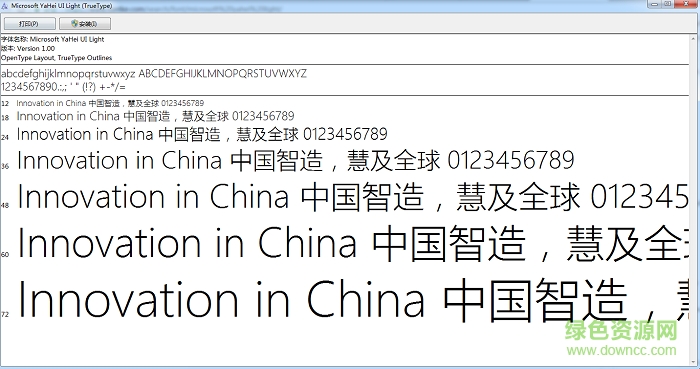
微軟雅黑light 適合數(shù)字英語么?微軟雅黑light字體有什么好處?微軟雅黑light文件是一款支持?jǐn)?shù)字和英文輸入的ttf格式微軟字體,light字體比標(biāo)準(zhǔn)的雅黑字體要細(xì)一些,更加纖美優(yōu)雅,用在雜志效果更好!
微軟雅黑的好處是放大多少倍字體之后看不到字體的毛邊還有的就是他的字體比較圓潤看起來比較舒服,現(xiàn)在微軟雅黑用得最多的應(yīng)該就是給手機(jī)刷字體了,因?yàn)槭謾C(jī)屏幕再大也就那5寸,所以看起來很舒服!